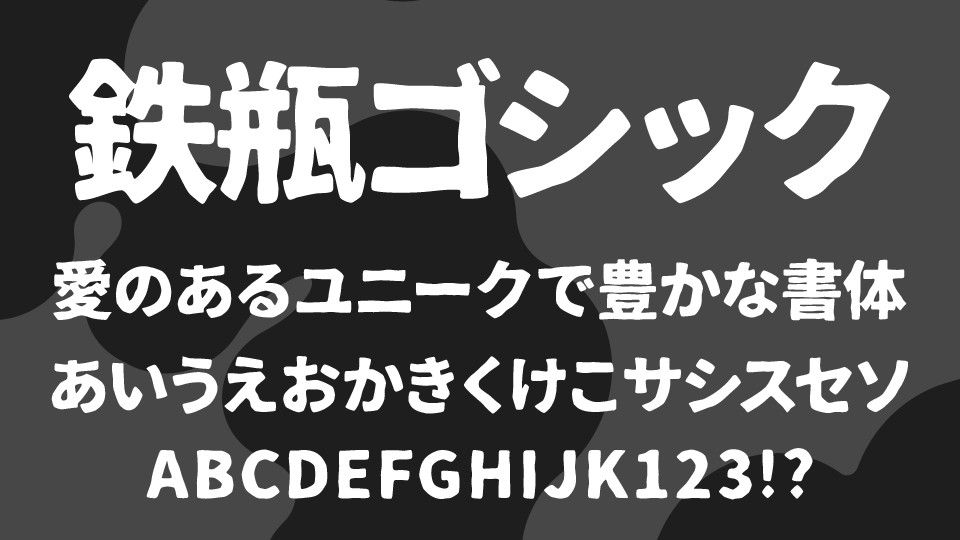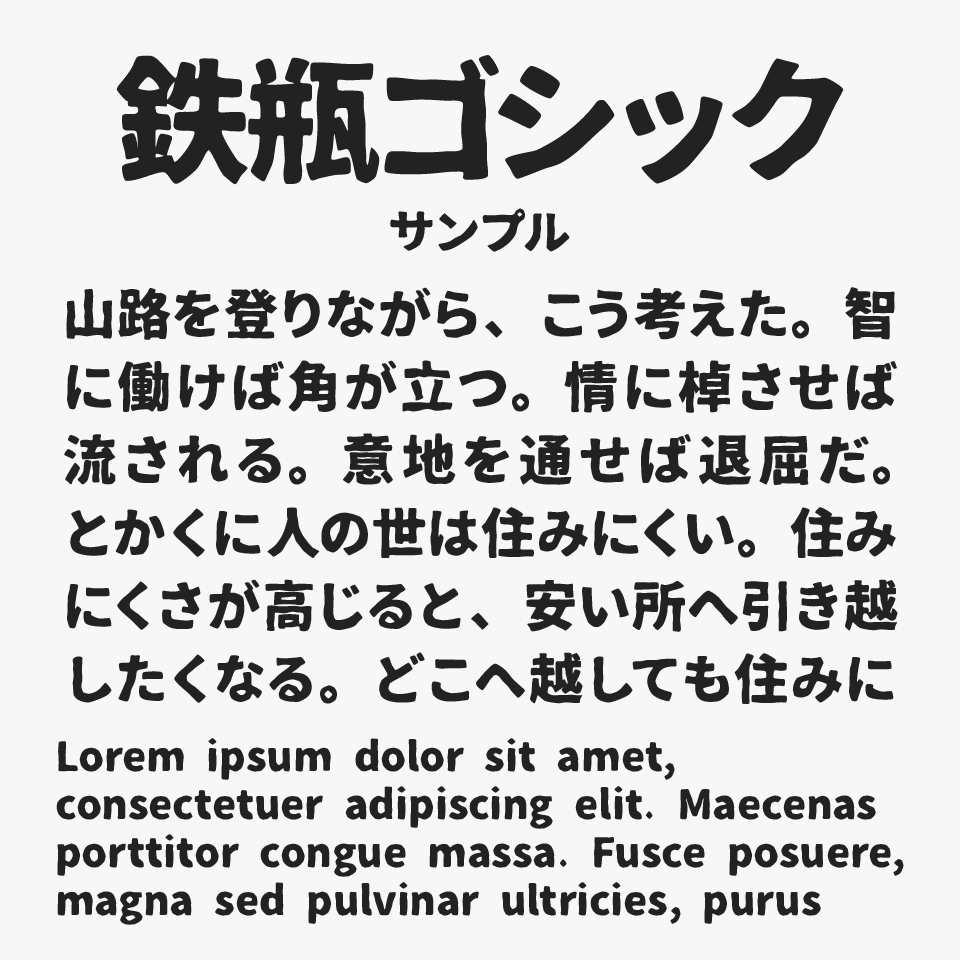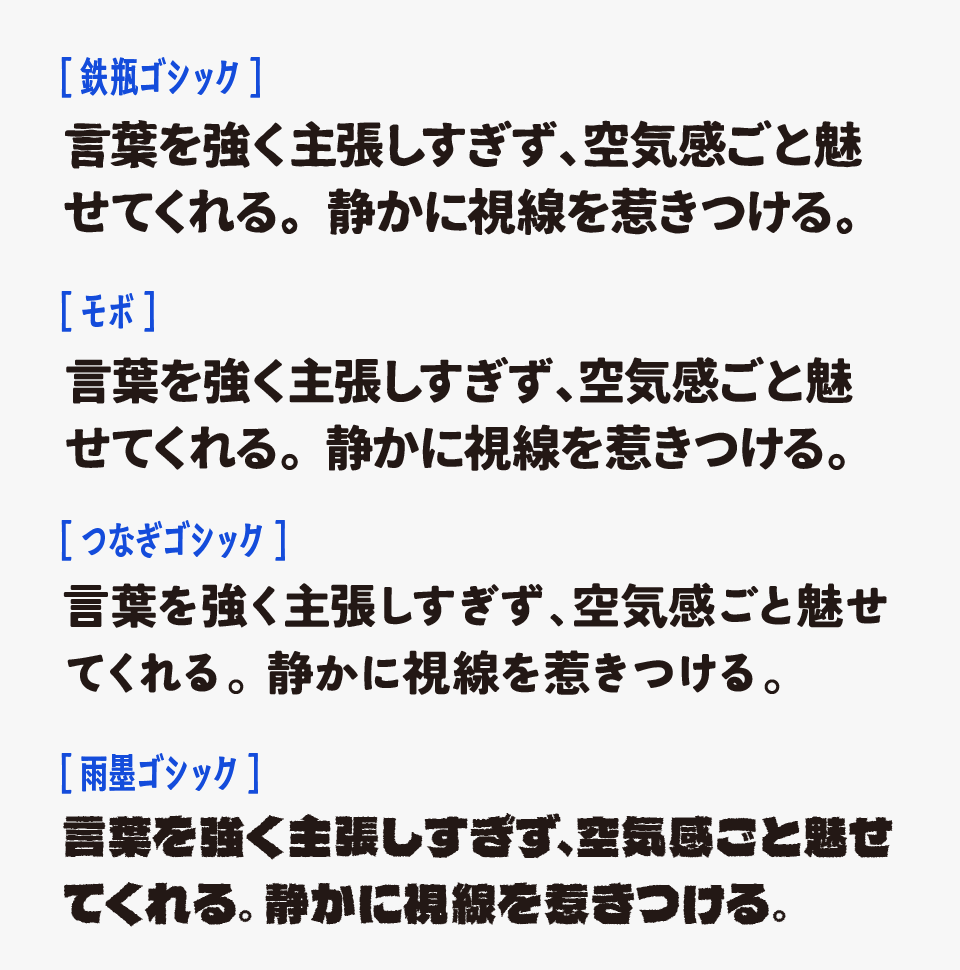
鉄瓶ゴシック
鉄瓶ゴシックフォントは、源ノ角ゴシックベースとして、極太でゴツゴツとした質感が特徴的な、味わい深いデザインゴシックフォントです。
どっしりとした力強さがありながらも、輪郭にはほんのりにじんだようなラフさが残されており、ゴシック体でありながら少し手書きぽさのある質感が温かみも感じられるユニークなフォントとなっています。
太さもあるフォントなので、見出しやタイトルなどに取り入れてみるとインパクトもあり、ゴツゴツ感が良い味がでます。使い方によっては少し主張が強い印象も感じることができます。
墨溜まりや滲みの質感を表現したほかのフォントと比較してみると、鉄瓶ゴシックは、ザラついたようなゴツゴツ感が特に印象的なフォントです。(比較フォントは、モボ、つなぎゴシック、雨墨ゴシックと比較しています。)
一般的な“かすれ系”フォントは筆の流れや滲みを強調したものが多いですが、鉄瓶ゴシックは、まるで金属や鋳物のような重厚感があり、無骨で荒々しい質感が魅力となっているフォントです。